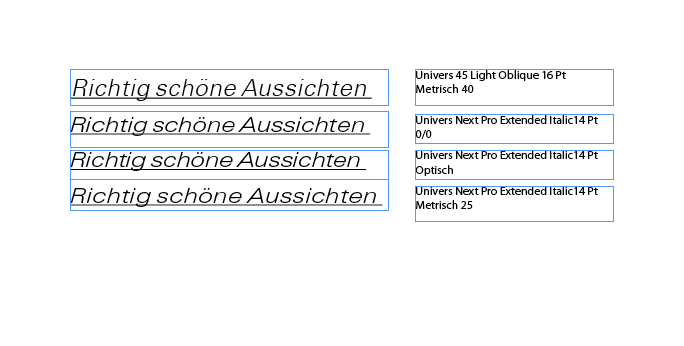
Breit/Extended Schriftschnitt was zu beachten beim Satz?
ich wollte generell fragen, man möge mir verzeihen, dass ich noch Neuling bin, ob es was zu beachten gibt beim Setzte von breiten/Extended Schriftschnitten?
Wurden sie für eine spezielle Anwendung, wie Überschriften/Plakate o.Ä gedacht?
Na ja, generell kann man sagen, dass solche Schriftschnitte dafür entworfen wurden, um aufzufallen, sei es als Texthervorhebung oder auch als Headline. Als Fließtextschrift eignen sie sich eher nicht, da sie zum einen anstrengender zu lesen sind als Book- oder Regular-Schriftschnitte, die ja extra für den Mengensatz gestaltet wurden. Zum anderen kannst Du Schriftstücke locker auf das Doppelte ausdehnen, wenn Du sie in einer so extrem breit laufenden Schrift setzt – das ist aus verschiedenen Gründen nicht sinnvoll (Kosten, Dokumentumfang …). :)
Also HL habe ich mir eher gedacht. Ich wusste nur nicht, ob es eine Faustregel gibt wie Laufweite muss/soll im Bereich +30 bis -30 (inDesign-Werte) bleiben o.Ä?
Hmmm, ich kenne keine Faustregel dafür. Ich würde sagen, das hängt von der jeweiligen Schriftart und ihrer Lesbarkeit ab. Ich sperre solche Schriftschnitte gegebenenfalls ein wenig. Wenn Du Versalien setzt, solltest Du – wie bei allen anderen Schriften allgemein auch – deutlich sperren, um einen ausgewogenen Laufrhythmus der Schrift zu erreichen. :)
Ich dachte es noch in Erinnerung zu haben, dass ein Dozent mir gesagt habe, man müsse die Lauftweite zwischen +30 und -30 halten, sonst wird der Schrift zu verzerrt...
Na ja, verzerren sollte man die Schrift auf gar keinen Fall. Aber die Laufweite, also die Abstände der Buchstaben, Ziffern und sonstigen Zeichen zueinander, sollte im Einzelfall angepasst werden, um ein optimales Schriftbild und Leseergebnis zu erzielen.
Wenn Du hier in der Forumssuche mal »Versalsatz« eingibst, dann wirst Du ganz viele hilfreiche Informationen versierter Kollegen zum Thema finden. :)
Hmmm, ich kenne keine Faustregel dafür.
Da widerspreche ich. Es gibt sehr wohl eine Faustregel für die optimale Laufweite. Sie lässt sich von der normalen Schrift ableiten:
Bei normalen serifenlosen Schriften entspricht der Zeichenabstand zirka der Strichstärke der Grundschrift (z.B. des gemeinen »i«). Bei zunehmendem Buchstabeninnenraum muss die Laufweite weiter gehalten werden, als Beispiel sind hier Extended-Schnitte genannt. Umgekehrt muss die Laufweite bei abnehmendem Innenraum kleiner sein. Kleine Schriften brauchen mehr Laufweite als grosse Schriften. Um 12 Punkt beträgt die Laufweite meist 0. :tutor:
Das heisst für Dich, daß die Laufweite für eine breite Schrift (grosser Buchstabeninnenraum) grösser sein muss, als wenn Du eine normale (Regular, Roman) Schrift verwendest.
Die i-Regel kenne ich ja. Ich dachte nur allgemein. Nun gilt dies auch für Logos?
Ich bin beim Überlegen, ob man ein Logo also doch nicht in Illustrator basteln soll, die Laufweite dort optimiert, diese in Pfad unmwandelt und dann vergörßert bzw. verkleinert die Verktor-grafik. Wäre es nicht sinnvoller, eine Wortrmarke in ihr jeweiliges Umfeld neu zusetzen, um ein optimales Ergebnis zu erzielen? Oder bleibt die Laufweite bei Wortmarken in Illu "optimiert" auch als Pfad :?
Grundsätzlich ist sowas aber Sache des Schriftgestalters ... wenn eine Extended aufgrund ihrer Formen eine erweiterte Laufweite erfordert, sollte die Metrik entsprechend angelegt sein, und der Typograf kann sich mehr oder weniger darauf stützen.
Klar gilt es das bei der verwendeten Schrift zu überprüfen, aber es ist nicht so, dass man da (bei guten Schriften) pauschal was aufsperren müsste.
Edit: meine Antwort war eine Reaktion auf "Perplex". Du bist mir zuvorgekommen :)
Logos: hier gilt wieder anderes als bei einem gesetzten Text oder Überschriften ... Oft sind Logo-Schriftzüge viel enger gesetzt und manuell optimiert, ein ensprechender Lesetext ist lockerer, und man gleicht bei brauchbaren Schriften nicht manuell aus.
Da hast Du natürlich recht. Deshalb wende ich keine pauschale Faustregel an, sondern werde nur im Bedarfsfall aktiv … :)
Was Logos angeht: Hier wäre es kontraproduktiv, wenn man durch bedarfsgerechtes Setzen der Schrift in unterschiedlichen Größen ein immer wieder verändertes Erscheinungsbild eines Logos verursachen würde. Ein Logo soll sich ja gerade durch ein unverwechselbares Erscheinungsbild einprägen.
Dagegen spricht auch, dass viele Schriften in Logos keine Satzschriften sind, sondern extra für diesen Zweck gezeichnet werden oder zumindest Modifikationen bestehender Schriften sind.
Eine Fehlerquelle wäre es außerdem: Was, wenn die Datei auf einem Rechner geladen wird, der die benötigte Schrift nicht zur Verfügung hat? Und der Schriftzug plötzlich in Arial dargestellt würde?
Bei den Logos großer Konzerne oder Marken gibt es im Einzelfall Ausnahmen. Da diese ihre Logos in sehr unterschiedlichen Größen benötigen (Riesige Hochhausplakate, LKW-Prints, Werbemittel, Briefbogen etc.), wird das Logo häufig in mehreren verschiedenen Varianten angelegt, bei denen jeweils die Schriftproportionen und die der Bildmarke perfekt auf den jeweiligen Verwendungszweck abgestimmt werden. Aber auch hierbei gilt, dass die Schriften in Pfade konvertiert und keine offenen Fonts weitergereicht werden. Neben allen formalen Problemen würde hierbei nämlich außerdem auch noch das Schriftlizenzrecht verletzt. Bei normalen Logos für kleinere und mittlere Unternehmen (für Geschäftspapiere, Web, Anzeigen, etc.) reicht in der Regel eine Gestaltungsvariante aus.
PS. Unterlängen wie bei »g« sollten beim Unterstreichen ausgespart werden oder die Linie braucht mehr Abstand zur Fusslinie, damit die Unterlängen nicht durchkreuzt werden.